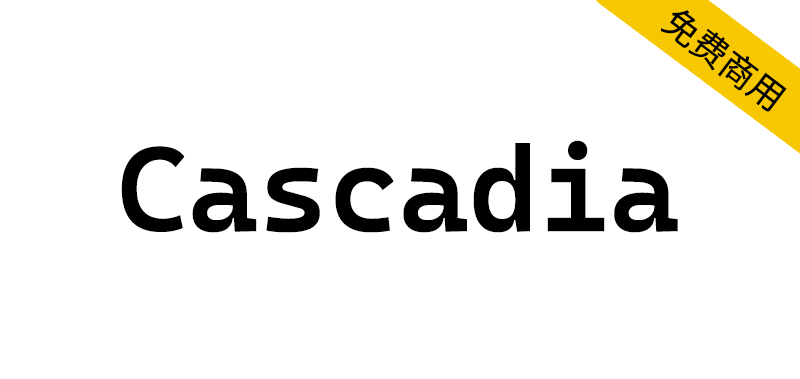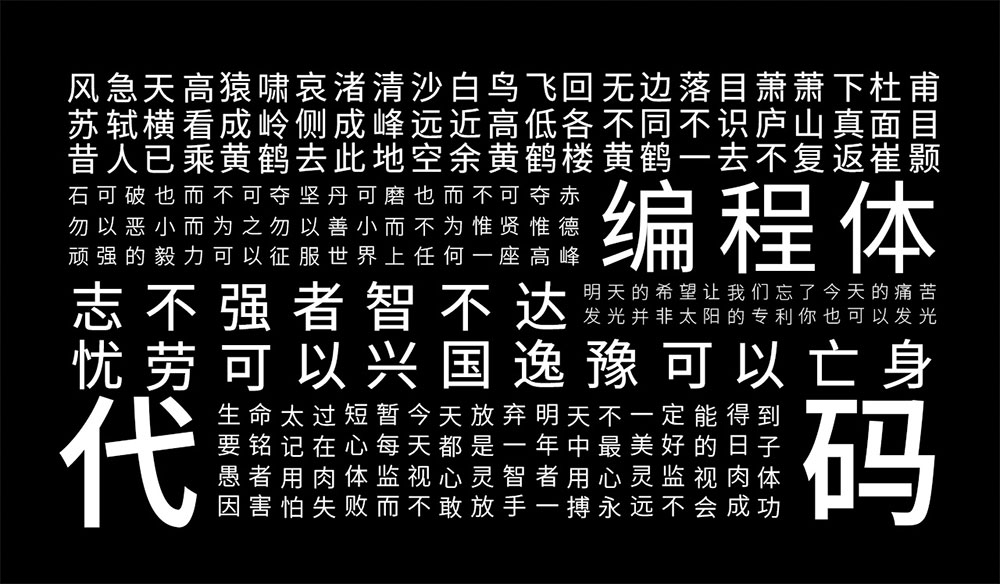
Cascadia是一种新颖有趣的新等宽字体,由微软精心打造,以其独特字形风格脱颖而出,它不仅专注于优化代码的可读性,使字母、数字和符号的辨认更为轻松,内置编程连字的独特设计,这一设计让用户在输入时,能够通过巧妙组合字符来创造出全新的字形,从而进一步提升了编程体验。专为提升Windows Terminal的现代视觉体验而打造,现已成为 Visual Studio 的默认字体。
○ Cascadia Code:Cascadia 的标准版本
○Cascadia Mono:无连字版本的 Cascadia
○Cascadia (Code|Mono) PL:内置 Powerline 符号的 Cascadia 版本
○Cascadia (Code|Mono) NF:内置 Nerd Font 符号的 Cascadia 版本
○Cascadia Next:为简体中文 SC(ASCII字符集 + GB2312扩展) 、繁体中文 TC(ASCII字符集 + BIG5+扩展) 和日语 JP(ASCII字符集 + 常用汉字 + JIS1/JIS2标准)特别打造,暂不支持阿拉伯语、希伯来语或NerdFonts符号集。
注意1:斜体版本包含标准斜体样式和可通过 ss01 启用的手写变体